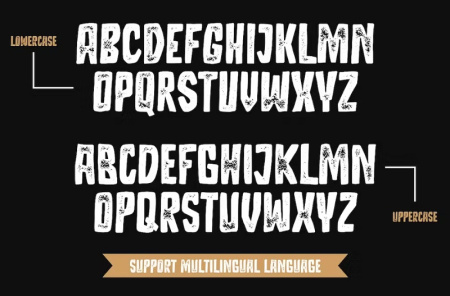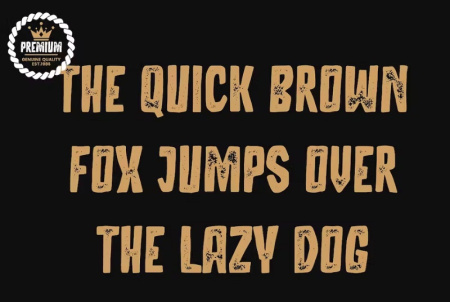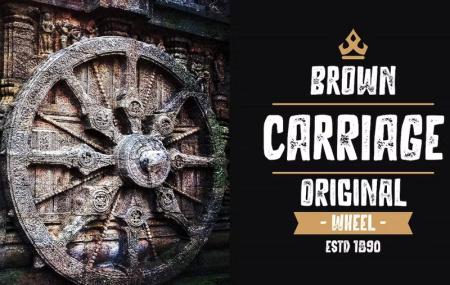
دانلود فونت انگلیسی مهر و استامپ Ribons
دانلود فونت انگلیسی مهر و استامپ
دانلود فونت انگلیسی مهر و استامپ Ribons با طراحی زیبا و مدرن. این فونت انگلیسی شامل نسخه های معمولی و مایل است. برای آرم ها، کارت نام، طرح بندی مجلات، دعوت نامه ها، سرصفحه ها یا حتی آثار هنری در مقیاس بزرگ عالی است.
✅ نام فونت انگلیسی: Ribons
✅ فونت تمام Caps
✅ علامت گذاری و شماره
✅ زبان چند زبانه